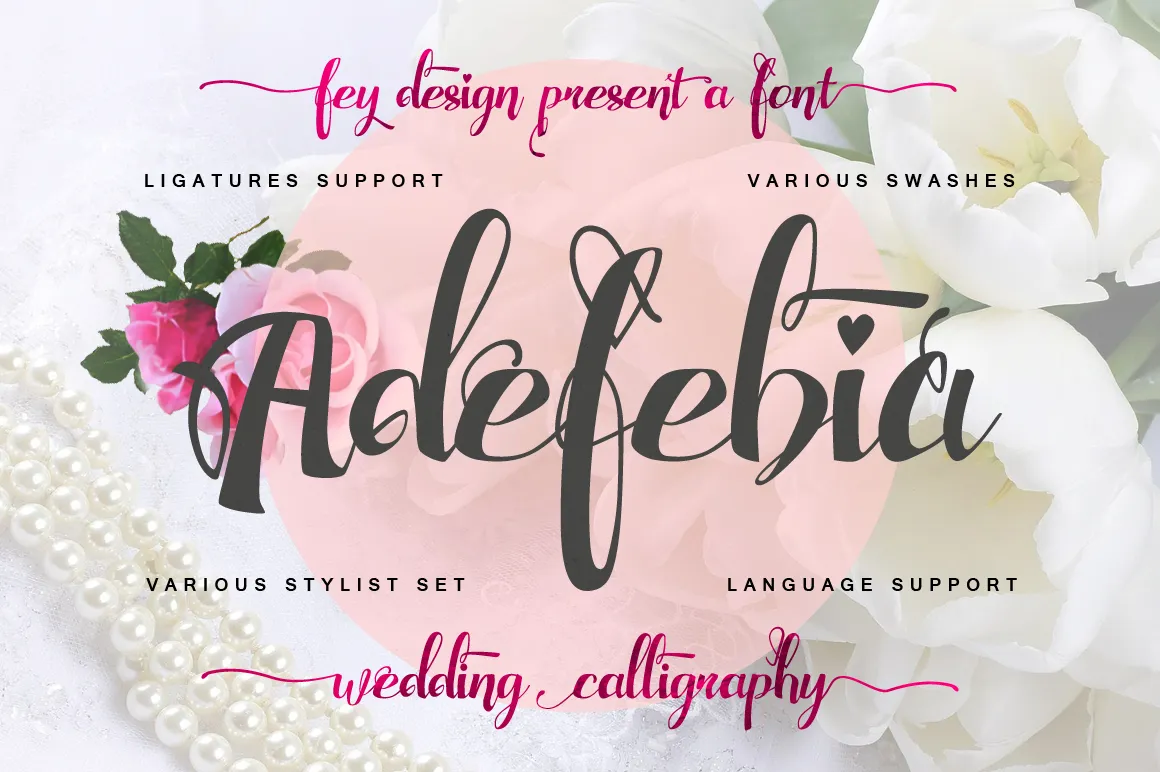
Adefebia Wedding Script Font – Download Grátis
A Adefebia Wedding Script Font é uma fonte script que se destaca no universo do design, especialmente para elementos românticos e festivos. Sujeitada a diversas aplicações como eventos de casamento, estampas de camisetas, logotipos e até mesmo artefatos impressos em etiquetas e cartões postais, ela oferece um toque especial que combina perfeitamente com o espírito do amor. Desenvolvida pelo designer Hamilton, a fonte é uma paixão de seus trabalhos mais pessoais e criativos, ideal para quem busca algo único e sofisticado para complementar projetos especiais. A definição de sua função se estende além da festa perfeita, tornando-se um recurso valioso para qualquer projeto que exigir uma escrita atraente e romântica, seja ela em t-shirts ou em logotipos.